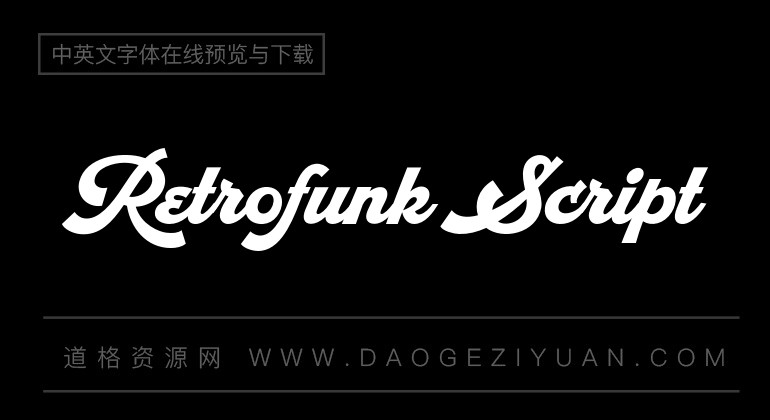
Retrofunk Script是一款带有复古风格的手写草书字体,其设计灵感来源于20世纪70年代的手写信件和海报艺术,具有非常明显的复古气息。 这款字体有着非常流畅的草书风格,字母之间的连结非常自然,同时也具有一定的艺术感。字母形状中包含了一些不规则的线条和装饰,使得整个字体看起来非常有趣和吸引人。 Retrofunk Script字体适用于广泛的场合,比如海报设计、广告设计、书籍装帧等等。如果你正在寻找一款凸显复古风格的手写字体,Retrofunk Script将是一个不错的选择。内容介绍
Retrofunk Script是一款非常不错的手写艺术字体,具有很好的视觉感,适合于文化类的宣传设计、商业类品牌的广告和产品包装设计以及个性化文字排版等较多场景。